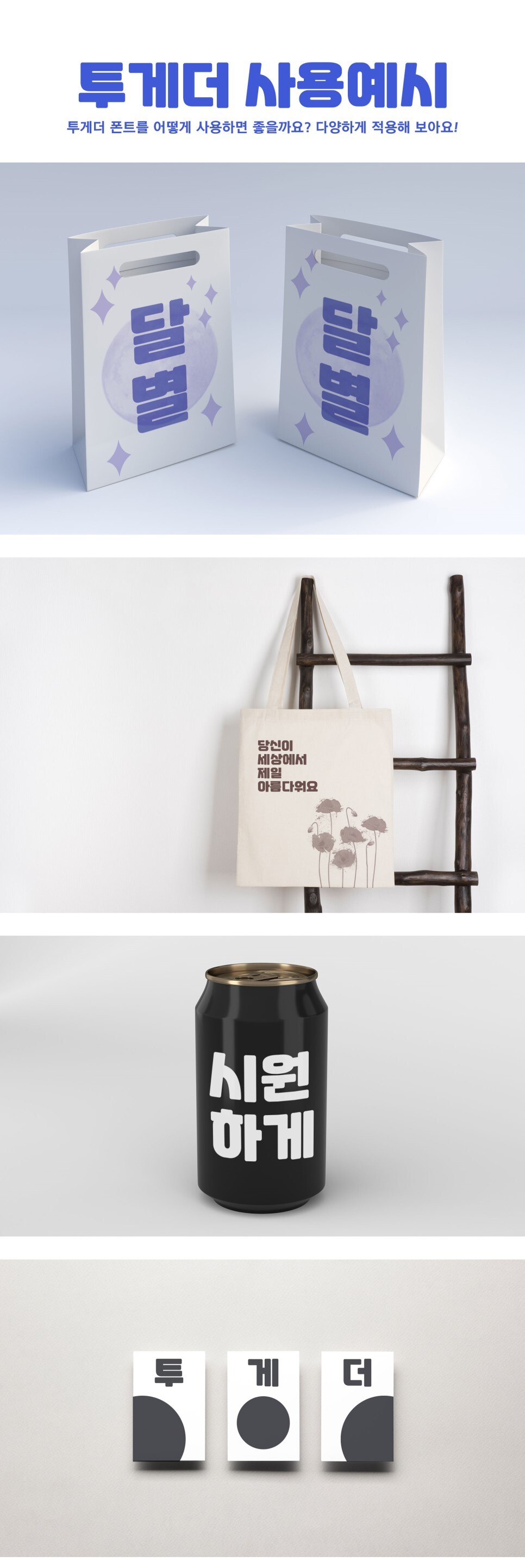
무료폰트(타이틀) : 투게더폰트
국내 최초 월1,000원의 파격적인 멤버쉽을 도입해 언제, 어디서나, 안심하고, 편리하게 사용할 수 있는 폰트를 지향하는 투게더 그룹에서 제공하는 무료폰트로서 단단한 헤드라인의 서체로 기본뼈대가 구성되어있으며 모든 외곽선에 굴림을 주어 친근한 이미지를 강조해 타이틀로 제격인 폰트입니다.